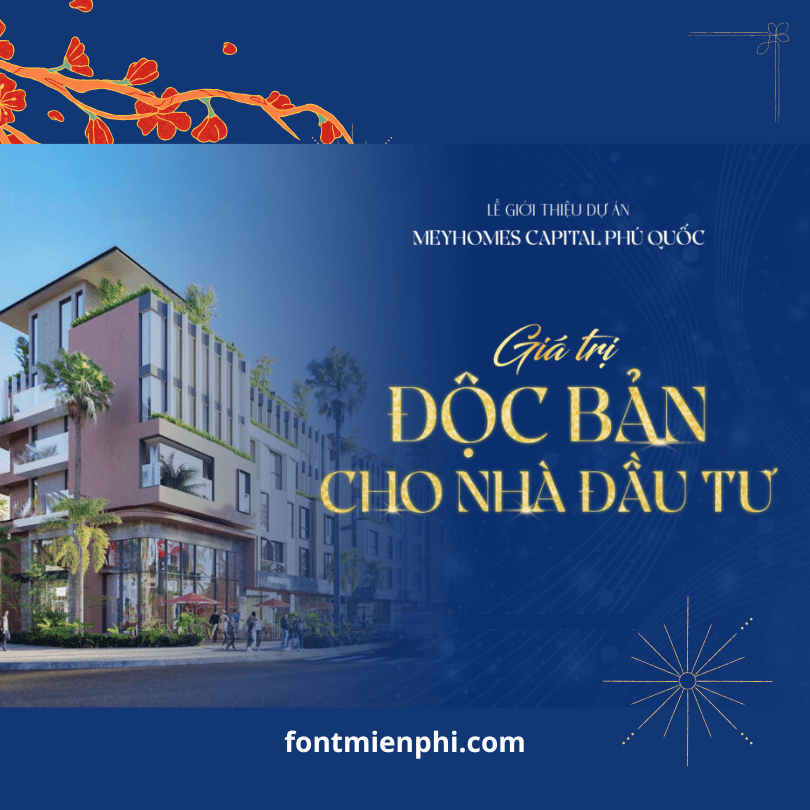
Combo font thiết kế Bất động sản
COMBO FONT THIẾT KẾ BẤT ĐỘNG SẢN CHUYÊN NGHIỆP
Dành cho dự án cao cấp – Tạo ấn tượng đẳng cấp
1. GIỚI THIỆU COMBO ĐẶC BIỆT
Bộ sưu tập font chữ chuyên nghiệp được thiết kế riêng cho lĩnh vực Bất động sản & Kiến trúc, kết hợp hài hòa giữa:
• Font chữ hiện đại phù hợp thiết kế brochure, catalogue
• Font chữ sang trọng cho banner, standee triển lãm
• Font chữ clean style ứng dụng digital marketing
2. COMBO FONT TIÊU BIỂU
2.1 FONT TIÊU ĐỀ NỔI BẬT
• Montserrat Bold – Phong cách tối giản nhưng mạnh mẽ
• Playfair Display – Nét thanh lịch đẳng cấp
• UTM Avo Bold – Font Việt hóa chuyên nghiệp
2.2 FONT NỘI DUNG CHUYÊN NGHIỆP
• Lato Light – Dễ đọc, phù hợp văn bản dài
• Roboto Regular – Hiển thị rõ ràng trên mọi thiết bị
• SVN-Gotham – Phong cách quốc tế
2.3 FONT NGHỆ THUẬT ĐẶC BIỆT
• 1FTV VIP Magiesta – Sáng tạo cho thiết kế cover
• UTM Beautiful – Nét chữ mềm mại quyến rũ
• SVN-Ariston – Sang trọng cho ấn phẩm cao cấp
3. ỨNG DỤNG THỰC TẾ
✔ Tài liệu giới thiệu dự án
✔ Banner quảng cáo triển lãm
✔ Thiết kế profile công ty
✔ Ấn phẩm digital marketing
✔ Hồ sơ năng lực doanh nghiệp
4. ƯU ĐIỂM VƯỢT TRỘI